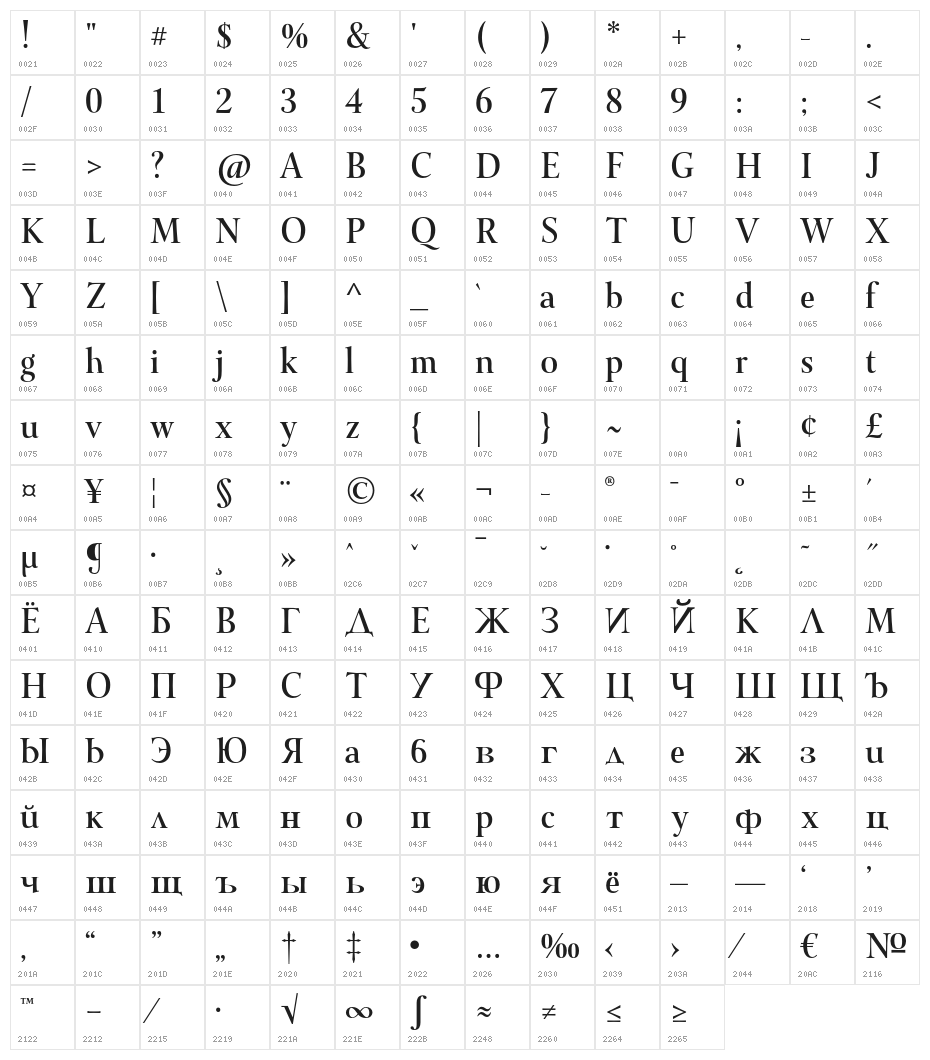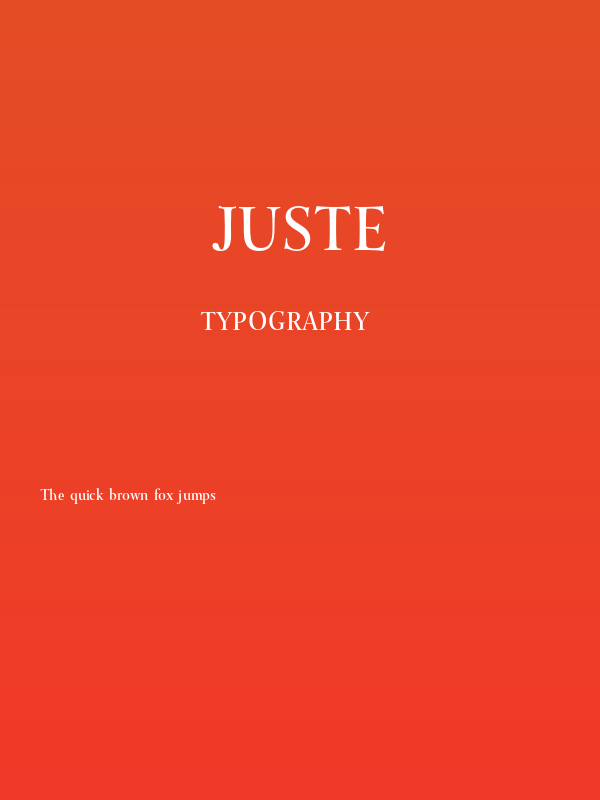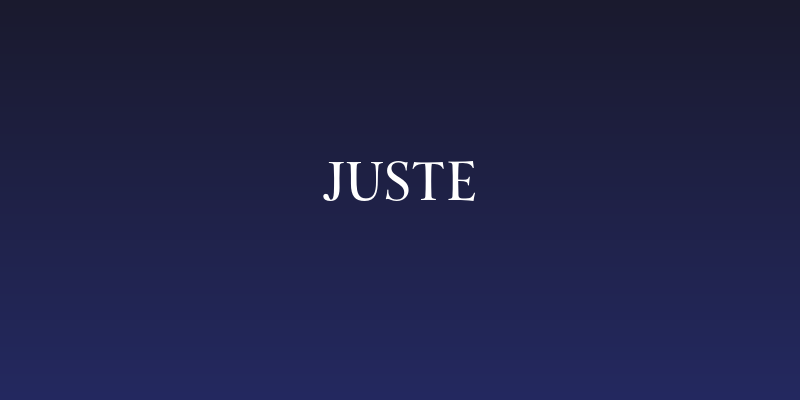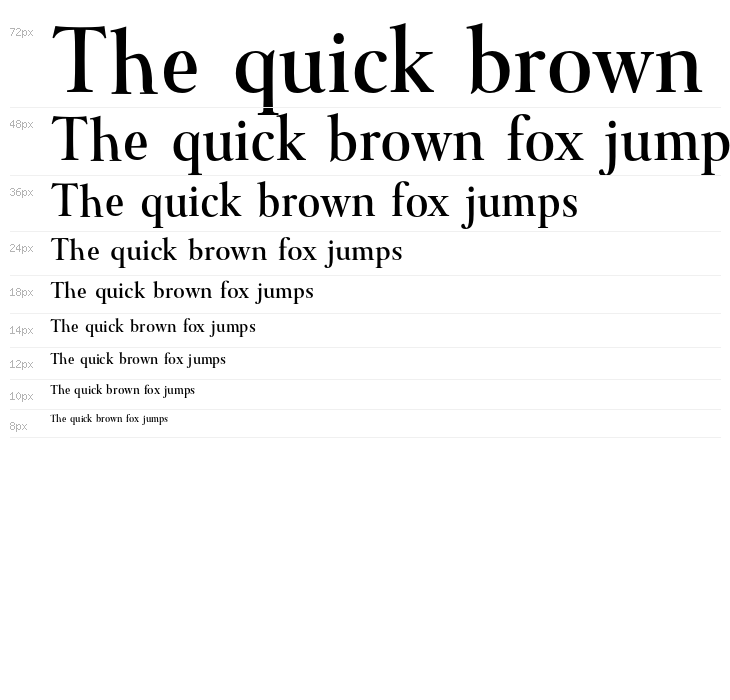
Juste Font
✎ Serif
| Progetti proposti | Ideal for editorial design, book covers, formal invitations, and branding projects that require a touch of elegance. |